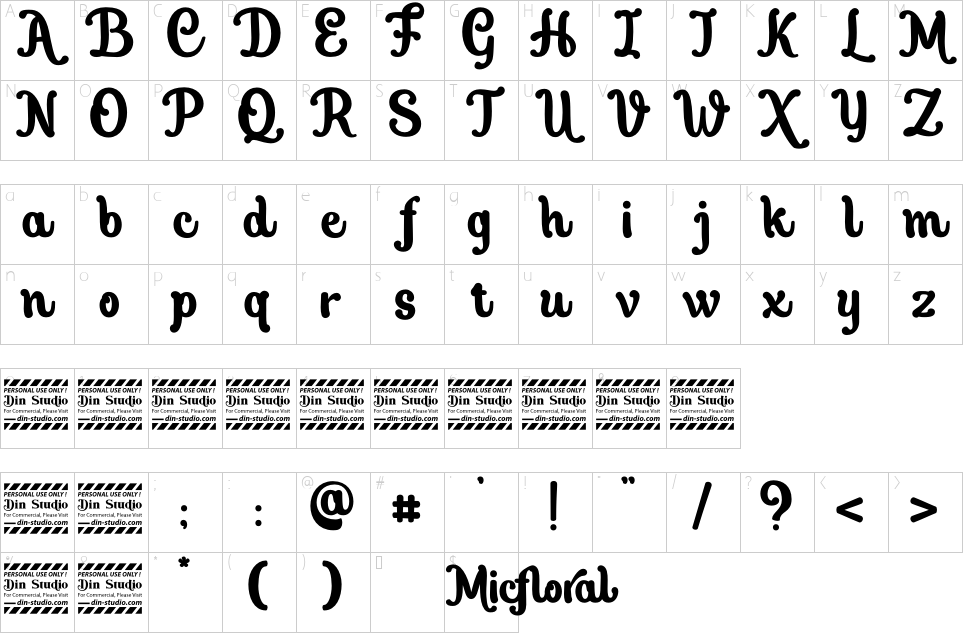
Micfloral é uma elegante fonte gráfica com traços fluidos e uma tipografia delicada, perfeita para criar designs envolventes e atraentes. Desenvolvida pela Din Studio, esta fonte é ideal para aqueles que desejam uma fonte personalizada para seus projetos de design gráfico. Com seu design cuidadosamente pensado, Micfloral oferece uma variedade de opções para estilos diversos. Desde letras suaves para nomes e títulos até linhas delicadas para códigos de marca e ilustrações. Essa fonte vem em versões para Windows e Mac, tornando-se acessível para designers de todo o mundo. Desde a sua introdução, a Micfloral tem sido amada por designers profissionais e amadores que desejam adicionar um toque único a seus projetos. Se você está procurando uma fonte de qualidade que não apenas complementa seus projetos, mas também os enriquece, Micfloral é uma excelente escolha.